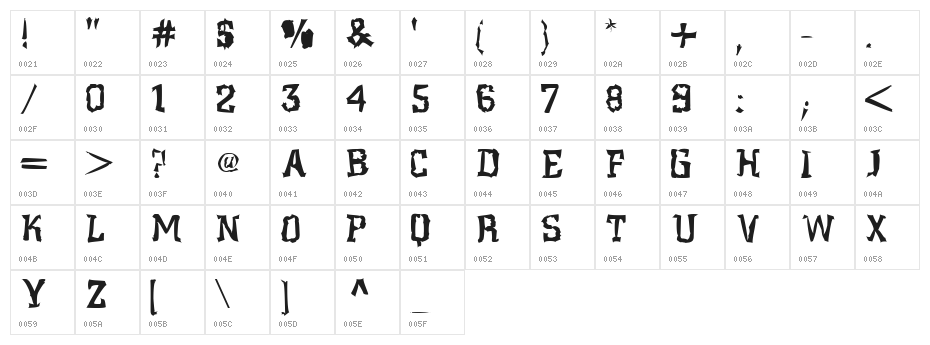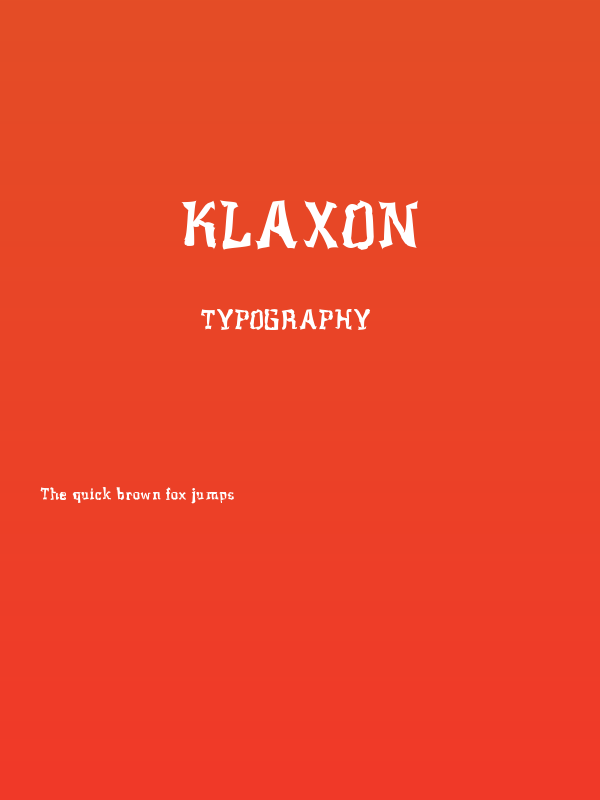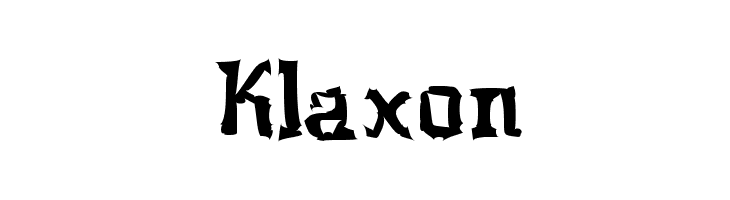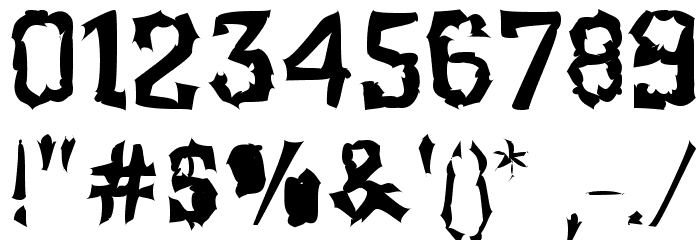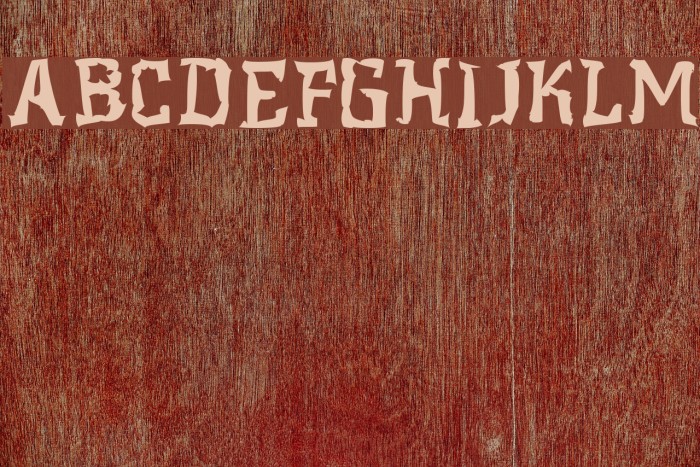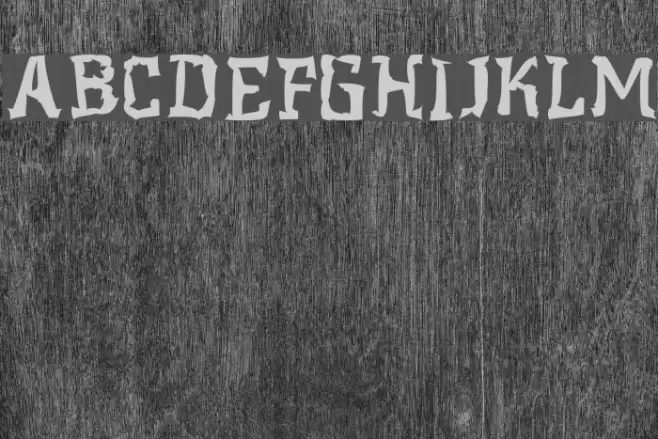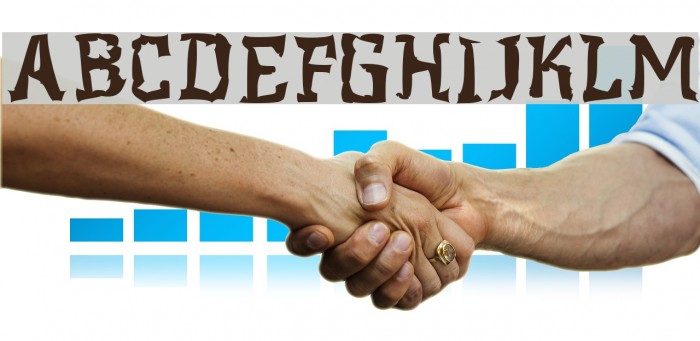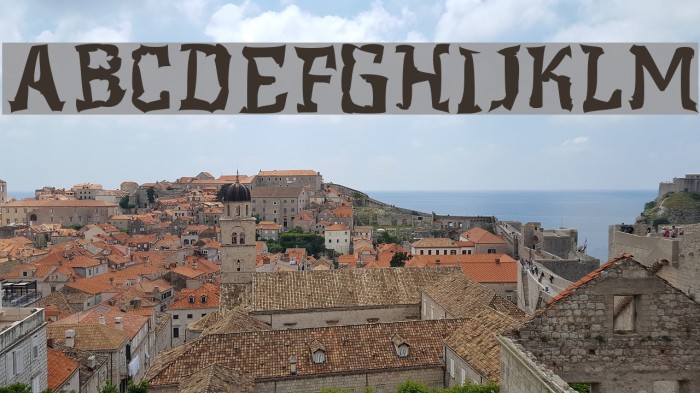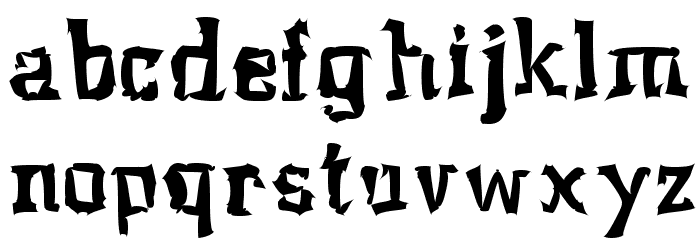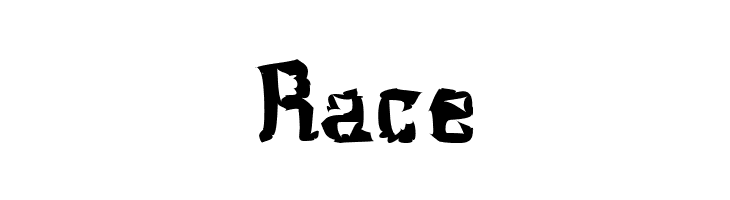
Klaxon Font
✎ Serif
| Anwendungsfall | Logos, Posters, Headlines |
| Vorgeschlagene Projekte | Ideal for horror-themed designs, rock band logos, edgy posters, and any project needing a bold, impactful typeface. |